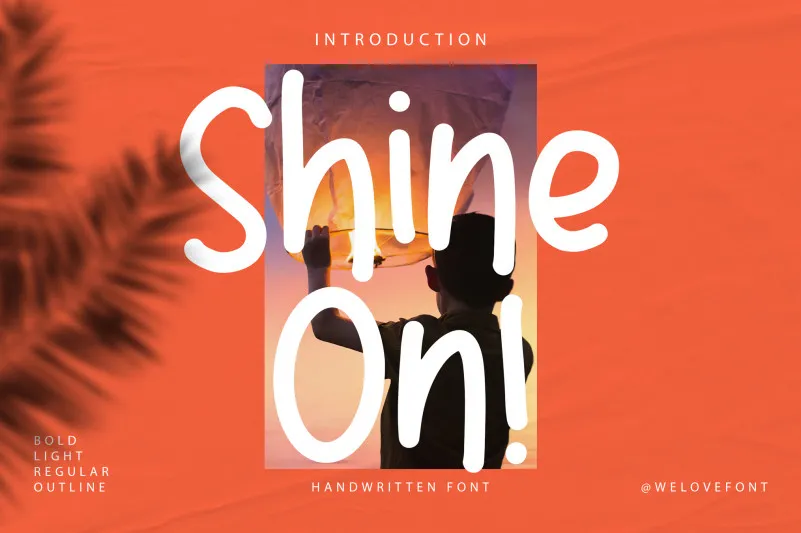
Shine on Font – Fonte Grátis
Shine on Font
A fonte ‘Shine on Font’ é uma fonte em estilo script que traz um tom leve e descontraído, criando um estilo encantador e aconchegante. Seja para aplicar em cartões de aniversário, gráficos personalizados ou até mesmo em designs profissionais, esta fonte oferece um toque único e divertido à sua biblioteca de fontes. Suas linhas finas e detalhes encantadores a tornam uma fonte versátil que pode revigorar qualquer projeto. Este é o tipo de font que você gostaria de ter na mão sempre, capaz de trazer um toque especial em cada trabalho que cria. Seja para uso pessoal ou profissional, Shine on Font certamente adicionará uma personalidade divertida e criativa a seus designs.
Designer: welovefont